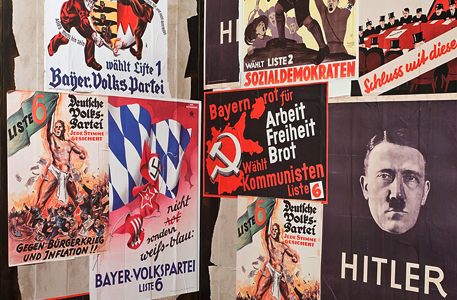
Von der »Typografie des Terrors« ist etwas reißerisch die Rede, wenn es um den Einfluss der Nazis auf die Schriftkultur geht. Tatsächlich wurden Typografie, Druck und Medien zwischen 1933 und 1945 in einzigartiger Weise instrumentalisiert.
Dies gilt in besonderem Maß für München, schon damals ein Zentrum des Druckgewerbes und mit Protagonisten wie Paul Renner, Jan »Iwan« Tschichold und El Lissitzky durchaus revolutionär eingestellt. Das sollte sich nach der Machtergreifung schnell ändern, nicht nur die Meisterschule für Deutschlands Buchdrucker wurde massiv »gereinigt«.
Die Nationalsozialisten erkannten sehr wohl die Möglichkeiten eines gesteuerten und gleichgeschalteten Schrift- und Erscheinungsbildes und nutzten dafür ihre Macht konsequent aus. Gelegentlich war dazu allerdings nicht sehr viel Zwang und Überzeugungsarbeit nötig.
Die Veranstaltung versucht, eine kritische Bestandsaufnahme der Situation in den 30er-Jahren zu schaffen. Verschiedene Fachreferenten beleuchten in Text und Bild die unterschiedlichen Aspekte des typografischen Schaffens unterm Hakenkreuz. …